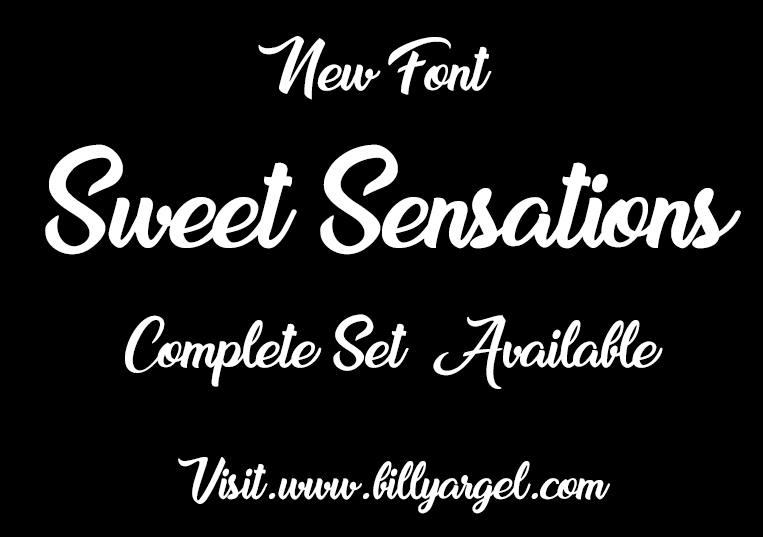
A Sweet Sensations Font é uma deliciosa coleção de letras para artes gráficas que traz à vida uma experiência única e envolvente. Esta tipografia está disponível gratuitamente para uso pessoal, permitindo aos artistas e designeres explorarem sua capacidade elegante e sofisticada em projetos como cartazes, editoriais de jornais ou até mesmo adereços para livros de arte. O criador desta fonte, Billy Argel, também oferece opções comerciais e completas para quem deseja utilizá-la de forma comercial. Pessoalizar sua marca pode não apenas tornar os projetos mais atraentes mas também expressar um toque único e personalizado. Para aqueles que desejam explorar ainda mais o universo da tipografia Sweet Sensations, visite o site oficial do designer para encontrar tudo o que precisa: billyargel.com. Aqui você encontrará mais informações sobre Sweet Sensations Font, bem como novas opções de design disponíveis a cada dia. Se tiver perguntas ou precisar de ajuda com qualquer coisa, Billy Argel está sempre disponível através do email .